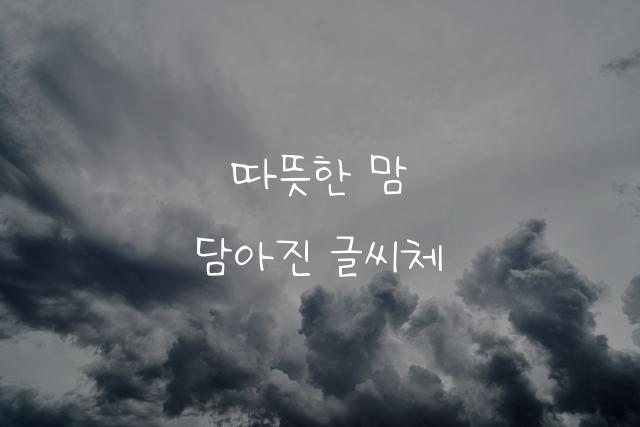
또박또박
‘또박또박’은 네이버에서 제작한 한국어 폰트로, 깔끔하고 선명한 획이 특징입니다. 이 폰트는 독서나 문서 작업에 이상적이며, 감성적으로는 안정감과 신뢰감을 줍니다.
네이버
1가지 굵기
한국어, 영어, 특수문자 지원
단정하고 깔끔한 느낌을 주면서도 따뜻한 인상을 남길 수 있는 목소리로, 전문적이면서 친근감을 제공합니다.
또박또박은(는) 계열의 생김새를 가지고 있으며
교육 자료, 보고서/문서, 일기/편지 등에서 자주 활용되며, 효과적인 메시지 전달에 적합합니다.
이 폰트는 교육, 출판/미디어, 공공/정부 분야에 잘 어울리며,
신뢰감, 명확한, 단순한 느낌을 담고 있는 것이 특징입니다.
이 폰트와 유사한 폰트로는 나눔고딕, 맑은고딕, 고딕체 등이 있어요. 함께 비교해 보시면 좋습니다!